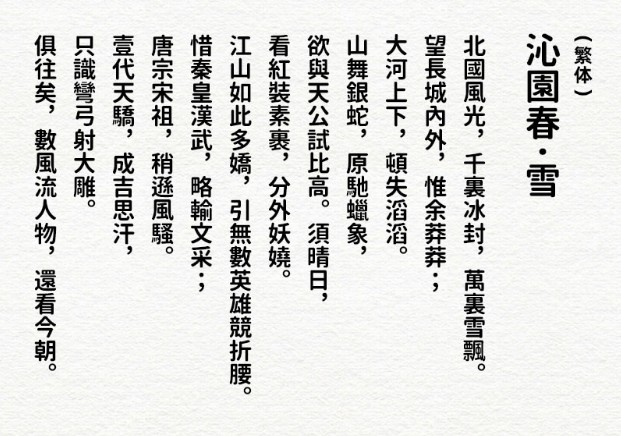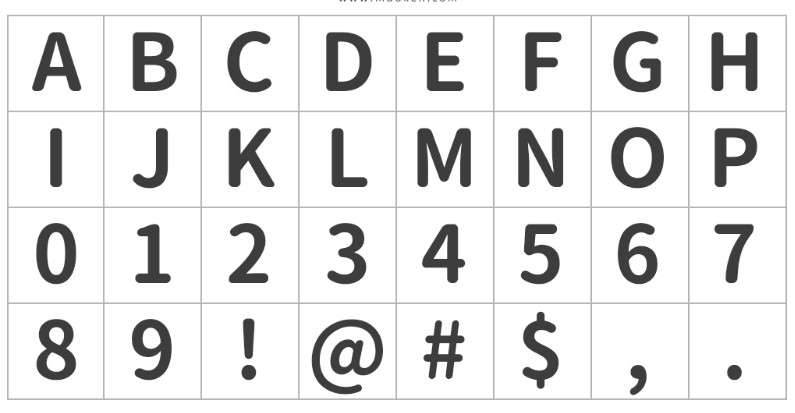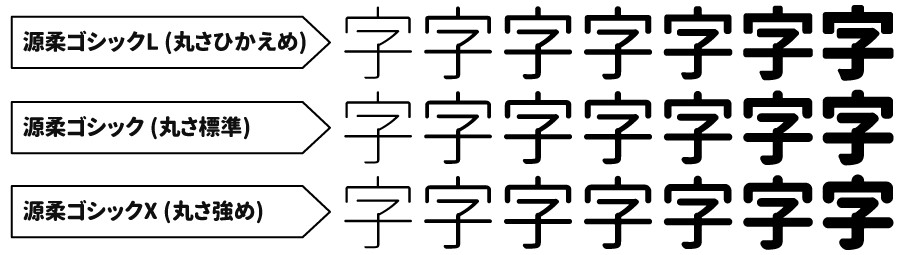
字体背景
国内很多网站都把这款字体叫做“思源柔黑体”,我觉得这个名称 并不太准确。因为这款字体是由日本网站“ 自家製フォント工房 ”制作发布的,并非Adobe和谷歌发布的官方字体。简体缺字比较严重。
为什么要纠结这个名字呢?是因为官方发布的思源系列字体,所支持的字符集非常全。而这款源柔黑体则是以日本版的思源黑体( 日文名:源ノ角ゴシック )为基础 制作衍生而成的字体,它的字符集是以日本JIS为标准的。所以这款字体对简体中文支持较差,但对繁体支持较好。所以猫啃网并不推荐使用这款字体。
字体特色
源柔黑体一共发布了3个版本,分别是标准版、L、X。它们的区别在于圆角的圆润程度不同,L圆角最小 (最尖),X圆角最大 (最圆),而标准版则是介于两者之间。每个版本都有7种字重,3种字形样式 (包括等宽字体),大家可以根据喜好选择使用。